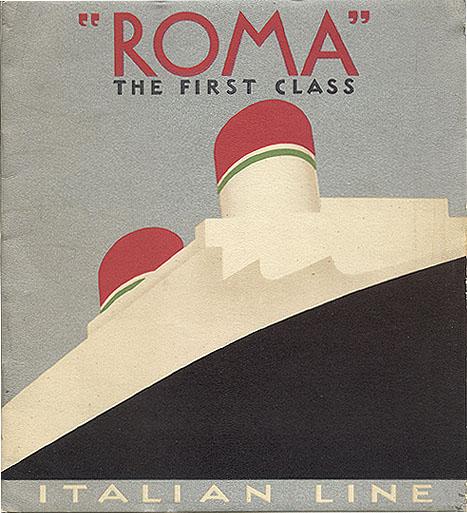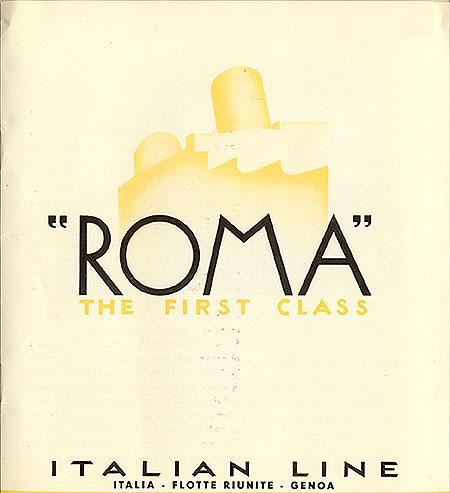
Suche Schriftart des Schriftzugs "Roma" auf Poster Italian Line
Ich habe das Bild auf luc.devroye.org gefunden, wo aber die zugehörige Schriftart nicht angegeben ist. Handelt es sich um eine Art-Deco-Schrift? Welche?
(Sorry, wenn ich zu viel Posts generiere.) Danke Ralf; ja, Lettering ist sicher plausibel. Aber ich fragte mich, ob die Formen des M, A und R nicht in bestimmten Schrifttypen (Art Deco?) vorkommen (möglicherweise nicht alle zusammen). Sie wirken irgendwie vertraut.
Die Formen des "ROMA" kommen sicher im Art Deco vor, während "ITALIAN …" mit seinen schrägen Enden nicht für die Art-Deco-Schriften steht. Dass genau diese Buchstaben aber einer Satzschrift entspringen, halte ich auch für unwahrscheinlich, zumal die beiden Schriftzüge "ROMA" auf Titel und Schmutztitel (?) sich unterscheiden.